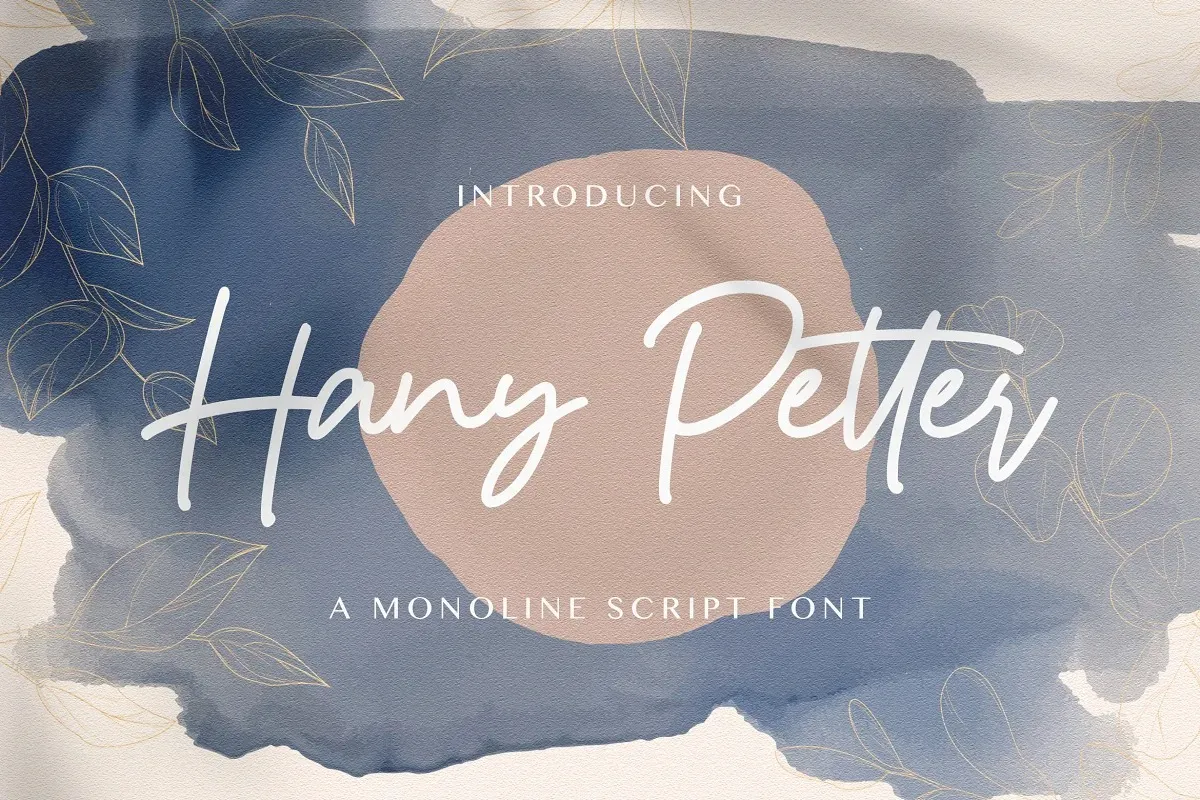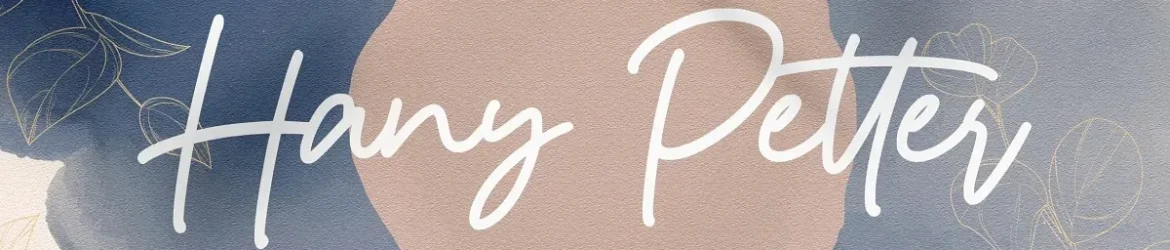
A Hany Petter Font é uma elegante e delicada fónt para assinatura, projetada por StringLabs. Suas letras são fluidas e bem equilibradas, criando um conjunto de caracteres que se adaptam perfeitamente a diversos estilos de design. Esta fonte é perfeita para quem busca criar ideias ainda mais atrativas, destacando-se com um toque único e sofisticado. Seja em cartazes ou designs digitais, adicionar esta fónt à sua estratégia criativa certamente fará seus projetos vibrarem ao vivo! Sua categoria de “Script Fonts” a torna versátil o suficiente para se adequar a uma ampla variedade de design, desde artes gráficas até editoriais.